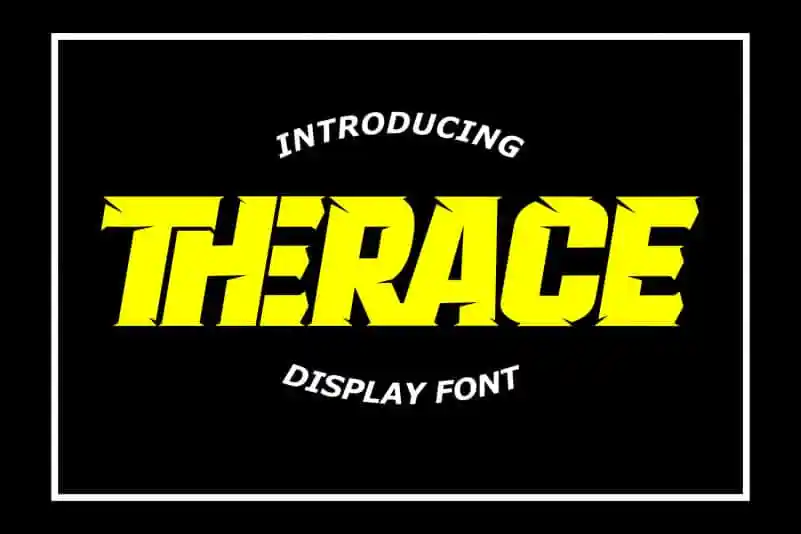
Therace Display Font – Download Grátis
A Therace Display Font é uma escolha perfeita para designers que buscam um estilo elegante e moderno na hora de criar logos ou marcas. Com seu design profissional, a fonte oferece letras largas e robustas, criando um impacto poderoso em qualquer aplicação visual. A Therace Display é ideal não apenas para logotipos e marcas, mas também para embalagens de produtos, apresentações e qualquer tipo de design gráfico. Seu designer habilidoso garante que a Therace se destaque em qualquer plataforma digital ou impressa. É uma fonte que realmente merece estar no seu portfolio, trazendo aos seus projetos um toque profissional e diferenciado.